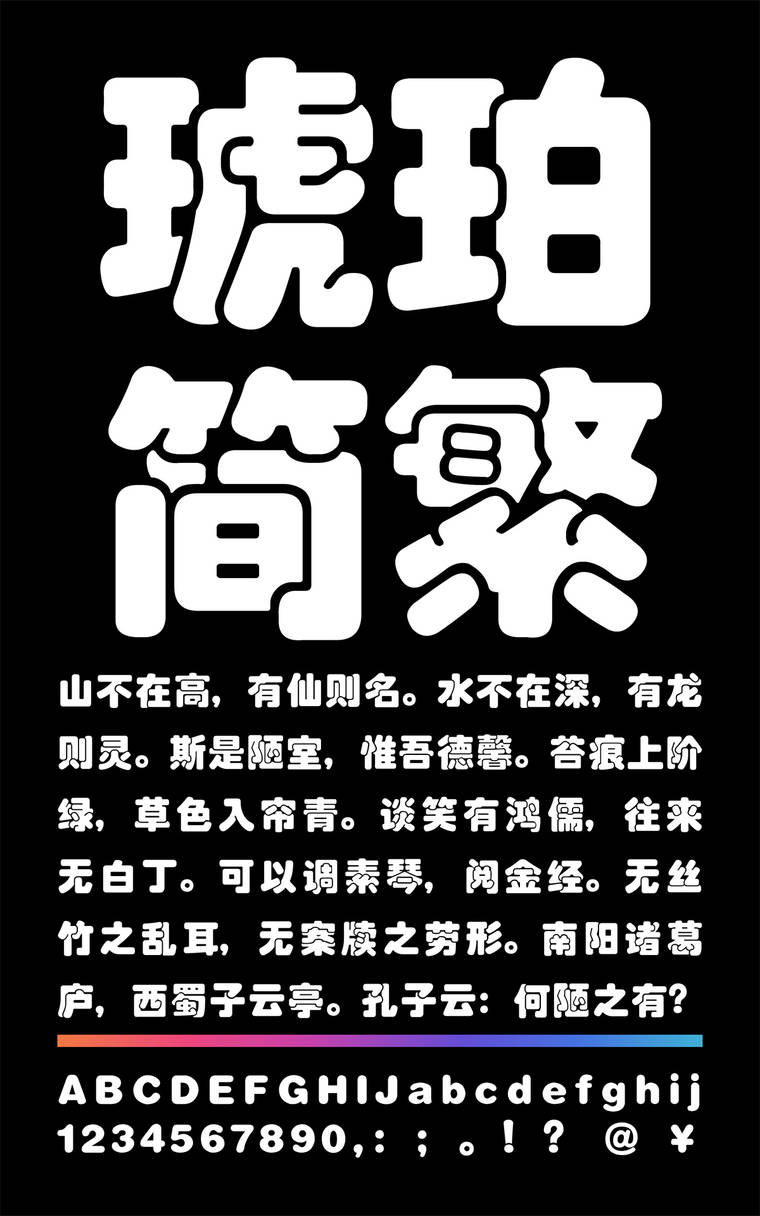
锐字云字库琥珀简繁
锐字云字库琥珀简繁,这款字体结构工整、笔画清晰,兼顾美观与易读性,适用于标题、正文、海报、包装、LOGO 等多种场景。字形优雅稳定,风格百搭耐看,适配日常排版与创意设计,让文字呈现更舒适、更具质感。锐字云字库琥珀简繁一笔一画,皆是细节,以均衡的比例、流畅的线条打造舒适视觉体验,字形端正大气,风格简约现代。无论是商业设计、品牌宣传还是日常排版,都能轻松驾驭,让文字更有格调与力量。锐字云字库琥珀简繁字体下载。
字体特征:字型圆润饱满,新颖活泼,粗而不重,胖而不臃,适用于书、报、杂志和各类印刷品的标题及装饰用字。